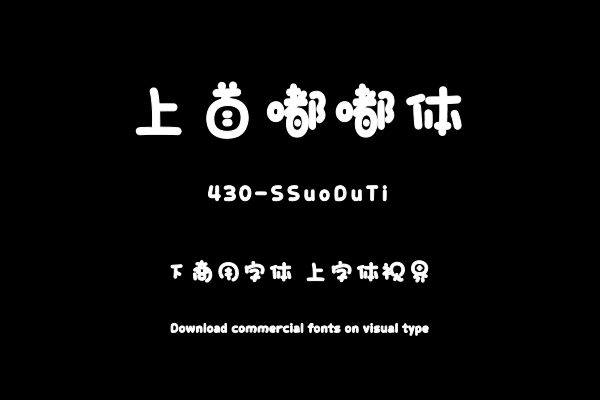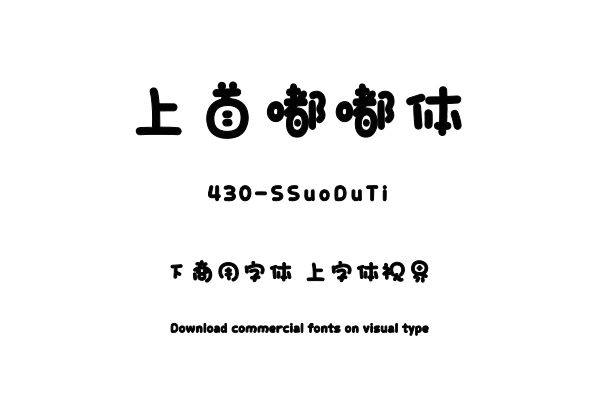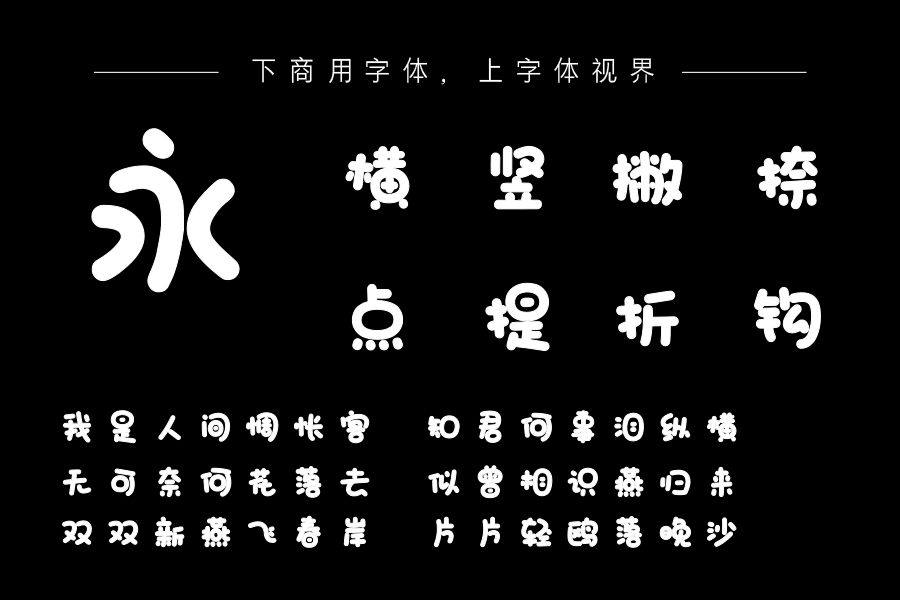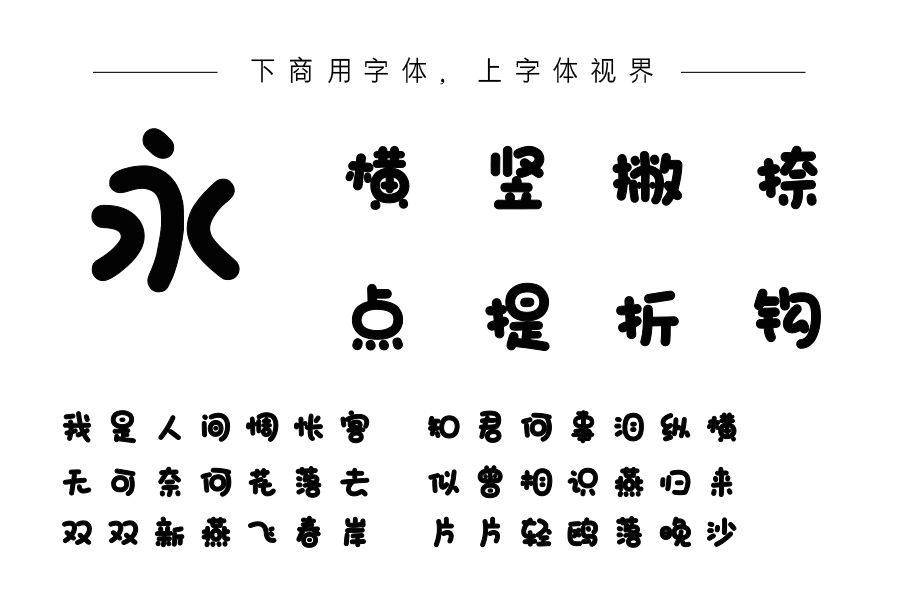
上首嘟嘟体,简体中文约6763字。这套字体笔画的圆润形态,如同给文字裹上一层柔软的 “情绪糖衣”,让其在视觉传达中自带亲和力;结构的灵动变形,恰似为文字赋予 “......购买须知:“下载服务费”与“字体VIP”所获得字体 仅用于个人非商用, 商用请联系付费授权。本字体为电脑用字,手机没有root权限不支持直接手机换字(手机如何root,请自行百度搜索教程)。购买前请先 了解清楚后再付款 ,字体为虚拟产品无法回收 一旦购买不支持退款。